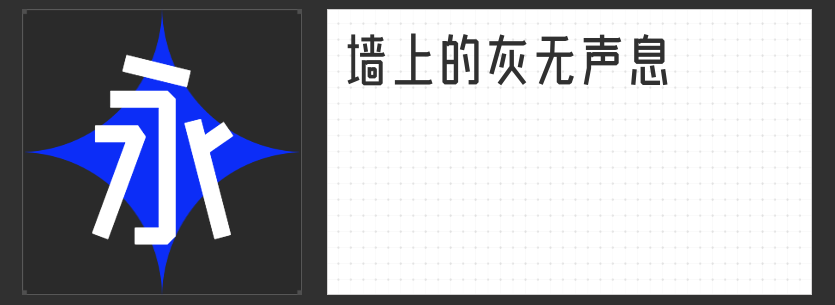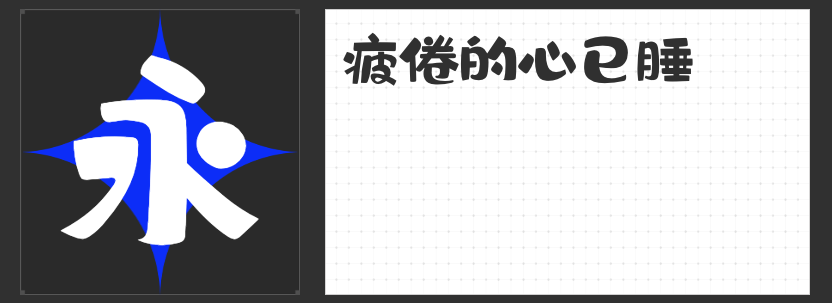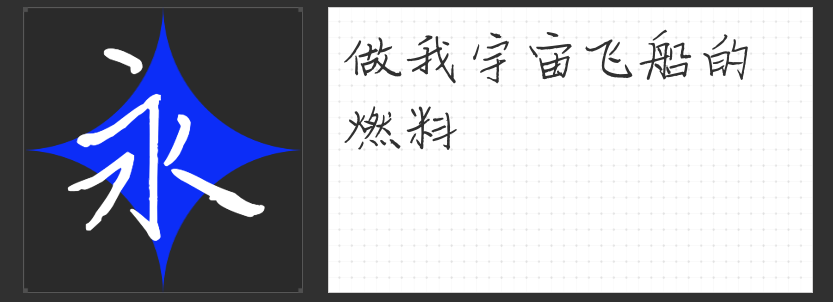
字体不会选?字节跳动签约四款字体供你参考!
励字造梦共创字库与字节跳动达成战略合作,首批签约设计师的字体作品已成功上线剪映、醒图中。这一合作不仅为创作者提供了更加丰富和个性化的字体选择,还标志着字体设计在数字内容创作领域迈出了重要一步。在这里,我们特别推荐四款签约字体。
1.励字玉树临风简
以其独特的韵味和流畅的线条,让人一见倾心。这款字体不仅适合正式场合使用,更能在日常设计中增添一份优雅与从容。它的每一个笔画都透露着自信与风度,仿佛字如其人,展现出一种从容不迫的气质。
2.励字憨憨简
则以其可爱的风格和憨态可掬的形象,赢得了众多用户的喜爱。这款字体线条圆润,整体风格亲切而友好,非常适合用在卡通、儿童读物或轻松愉快的设计中。它不仅能传递出温暖和欢乐的气息,还能让用户在看到字体的第一眼就感到愉悦。
则是一款充满个性的字体。它的笔画粗细适中,线条流畅而富有力量感,给人一种稳重而不失时尚的感觉。这款字体适合用在时尚、潮流或创意设计中,能够很好地突出主题,吸引用户的注意力。
以其独特的书法韵味和行云流水般的书写风格,赢得了众多书法爱好者的青睐。这款字体结合了传统与现代的特点,既有书法的古朴韵味,又不失现代设计的时尚感。无论是用在书法作品、广告设计还是其他需要展现文化底蕴的场合,都能起到画龙点睛的效果。
这四款字体各具特色,每一款都有其独特的魅力和应用场景。励字共创字库与字节跳动的合作,不仅让这些优秀的字体作品得到了更广泛的应用,也为广大创作者提供了更多灵感和选择。快来试试这些字体,为你的设计增添一份独特的魅力吧!